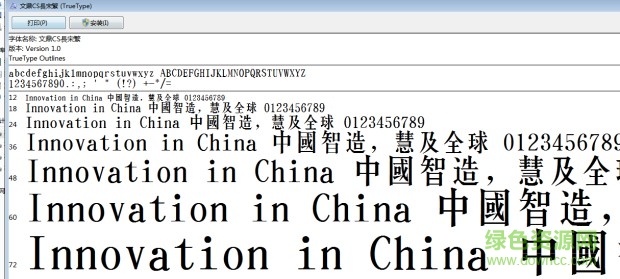
chunsungcseg bold t gb
chunsungcsegboldtgb字體是一款文鼎CS長(zhǎng)宋字體,字形修長(zhǎng)優(yōu)雅,造型規(guī)劃嚴(yán)謹(jǐn),線條細(xì)致美觀,用在排版、雜志、期刊、廣告等各個(gè)領(lǐng)域,歡迎大家免費(fèi)下載!
長(zhǎng)宋字體特點(diǎn)
長(zhǎng)宋體較一般宋體細(xì)長(zhǎng),有立體感。常用于排印詩(shī)詞文集,還用于排印古籍書。
chunsungcseg bold t gb